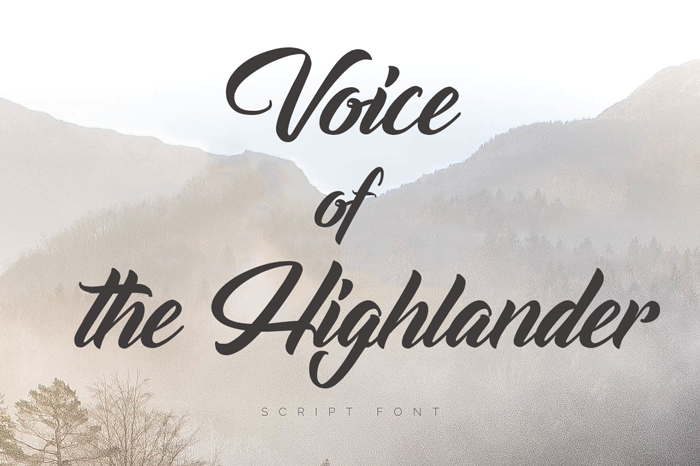
Voice of the Highlander Font – Download Grátis
A Octotype oferece a você a oportunidade única de adquirir a Fonte ‘Voice of the Highlander’ — uma elegante fonte script que se destaca por sua personalidade fluida e encantadora. Essa fonte é perfeita para o texto da web, cartões de aniversário, logotipos, e muito mais. Com seu design cuidadosamente construído, a ‘Voice of the Highlander’ captura os sentimentos delicados do idioma e transforma-os em letras que vibram com vida. Perfeito para uma aplicação criativa ou um projeto personalizado, este é o selo perfeito para dar ao seu design aquele toque único e sofisticado. Com a fonte ‘Voice of the Highlander’ da Octotype você pode se beneficiar de sua completa versão do produto junto com um licenciamento comercial. Para obter mais informações sobre como adquirir esta incrível fonte, entre em contato através do endereço .